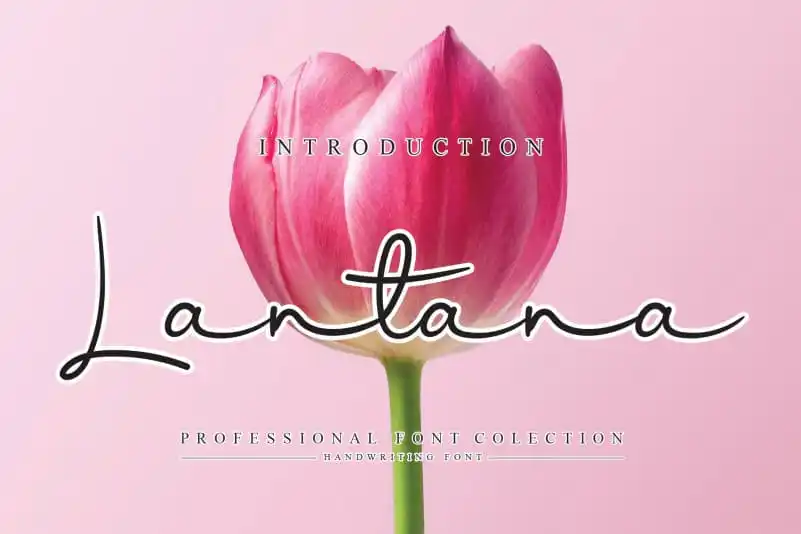
Lantana Script Font – Download Grátis
A Lantana Script Font é uma bela e romântica fonte escrita a mão que traz consigo um ar encantado e sonhador. Perfeita para criar uma atmosfera mágica nas suas criações, este tipo de texto retrata o estilo elegante dos convites de casamento, cartões de agradecimento, cartazes com frases inspiradoras, cartões de felicitação, logotipos e até mesmo as identidades corporativas. Seja qual for o projeto que você estiver desenvolvendo, este fonte entrega um toque único e inconfundível, sem comprometer a sofisticação necessária para qualquer design. A Lantana Script Font é uma escolha ótima para quem busca trazer um ar romântico ao seu trabalho de design. E mais importante ainda, ela vem do talentoso designer andikastudio que certamente não decepcionará com sua expertise em criações a mão.